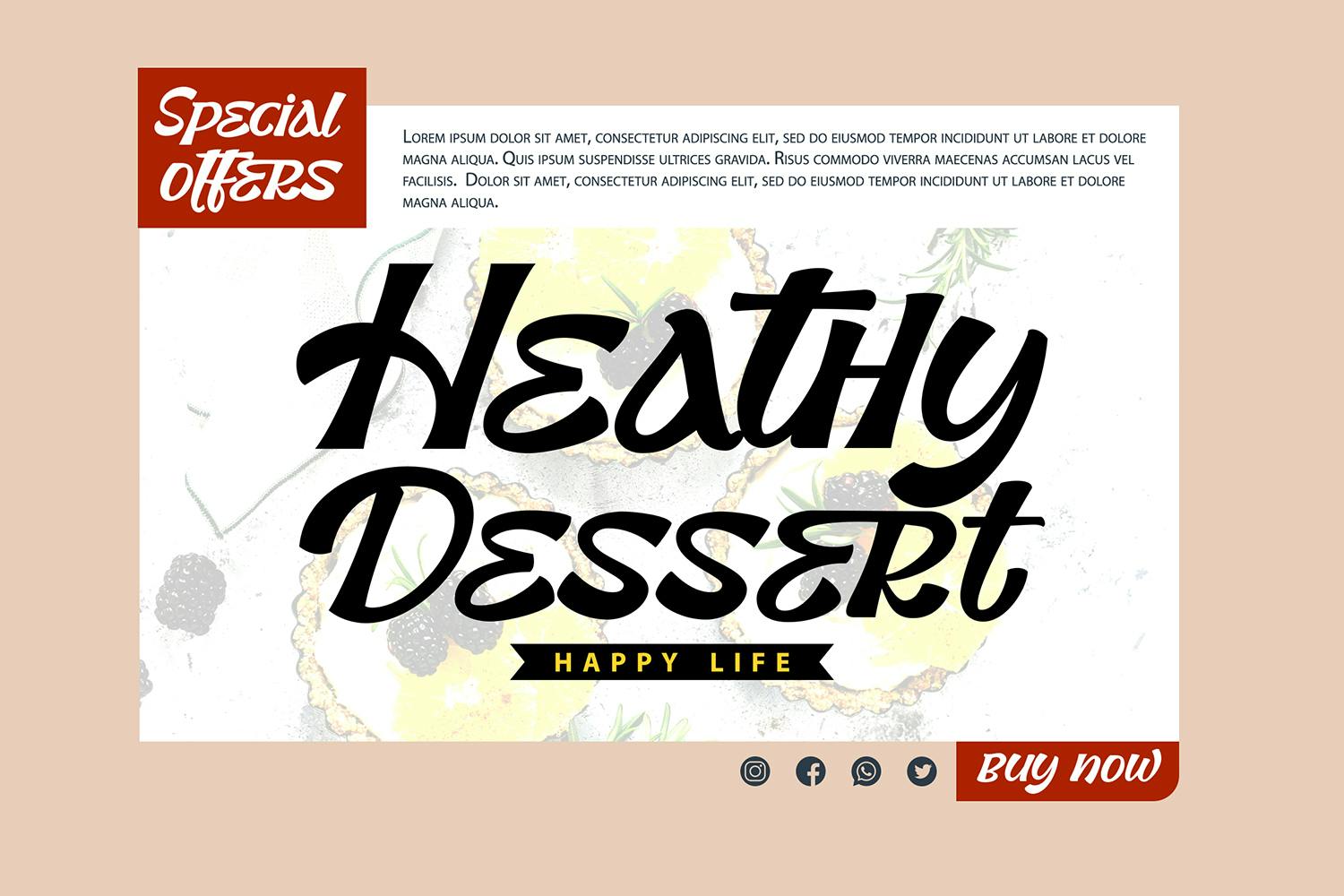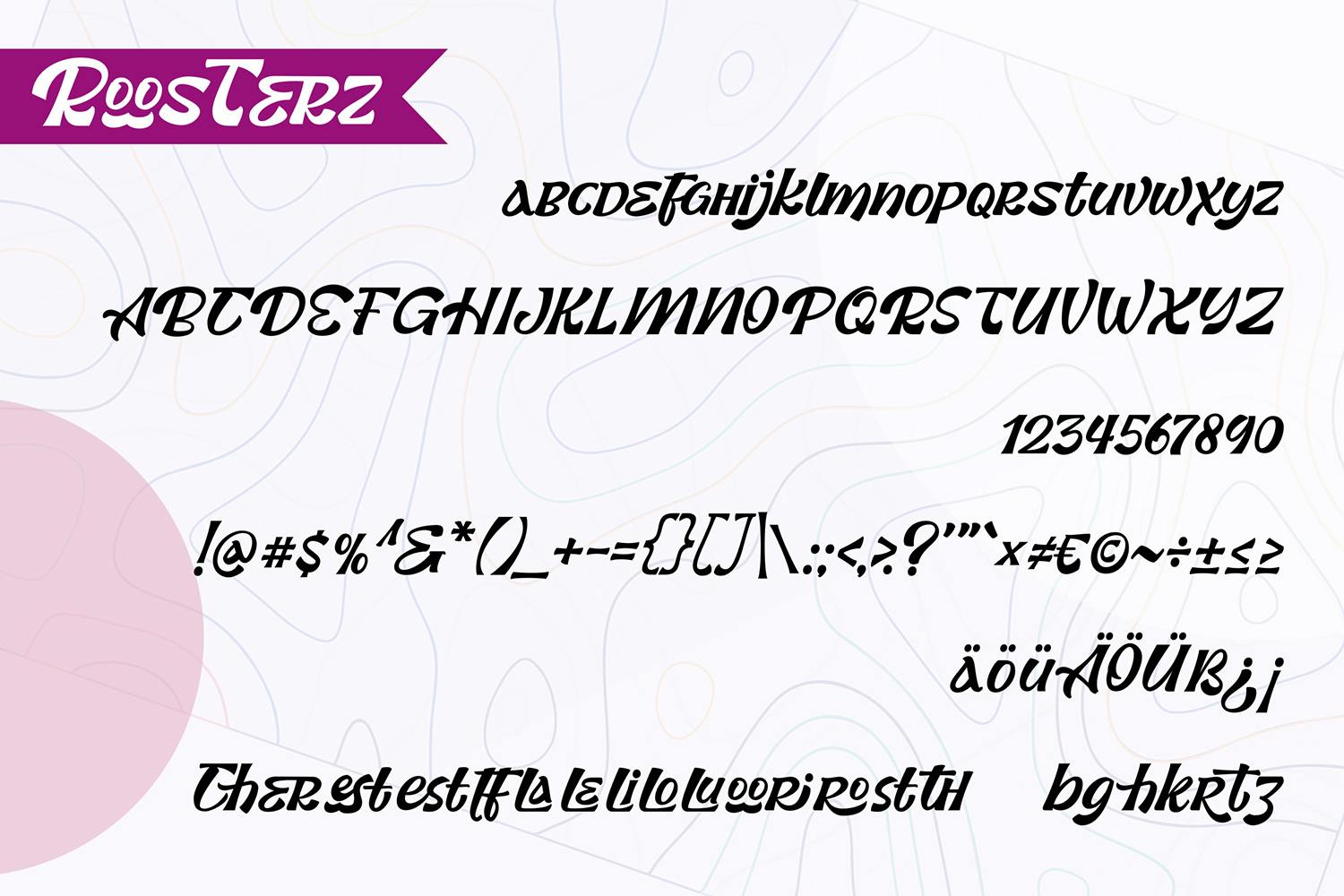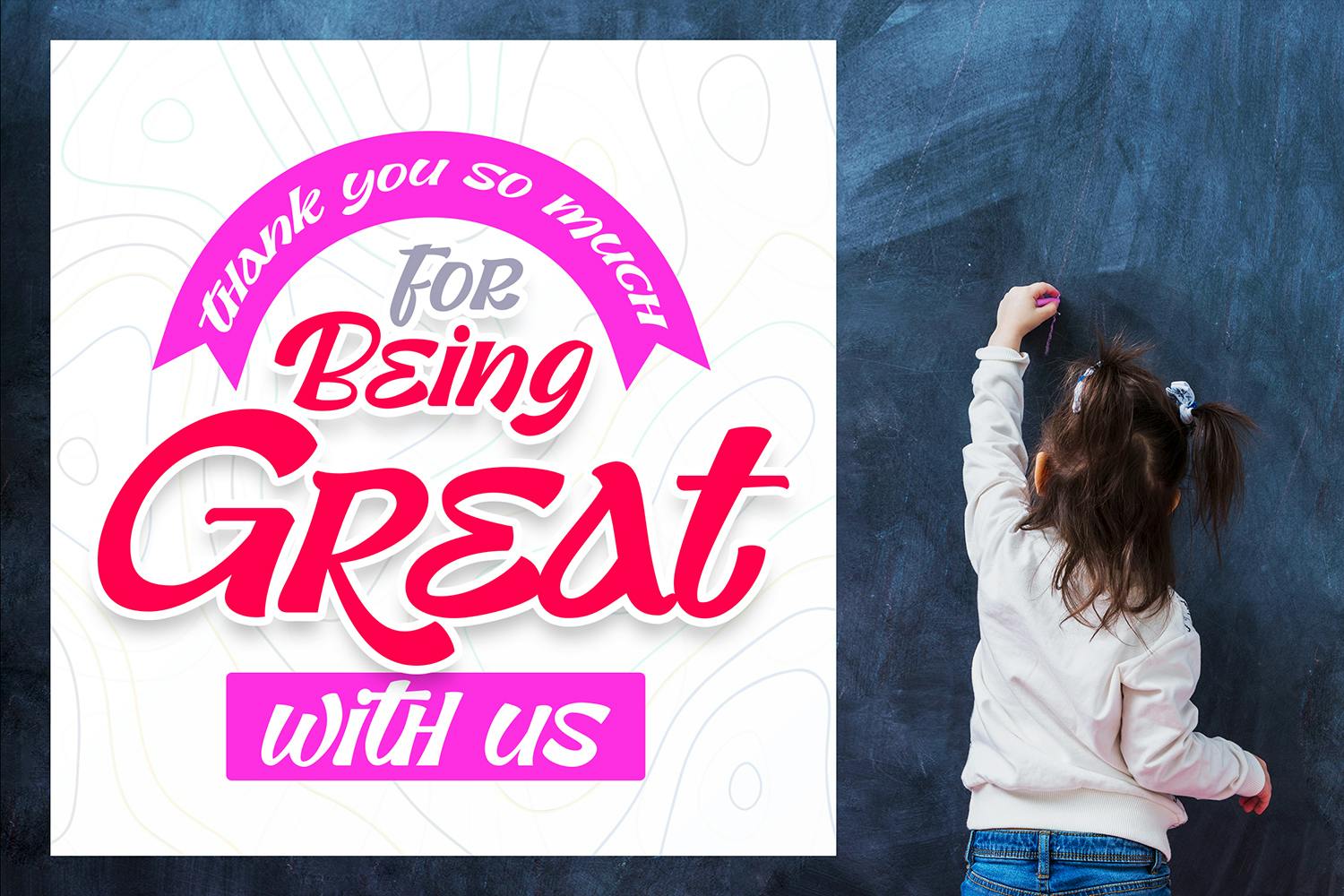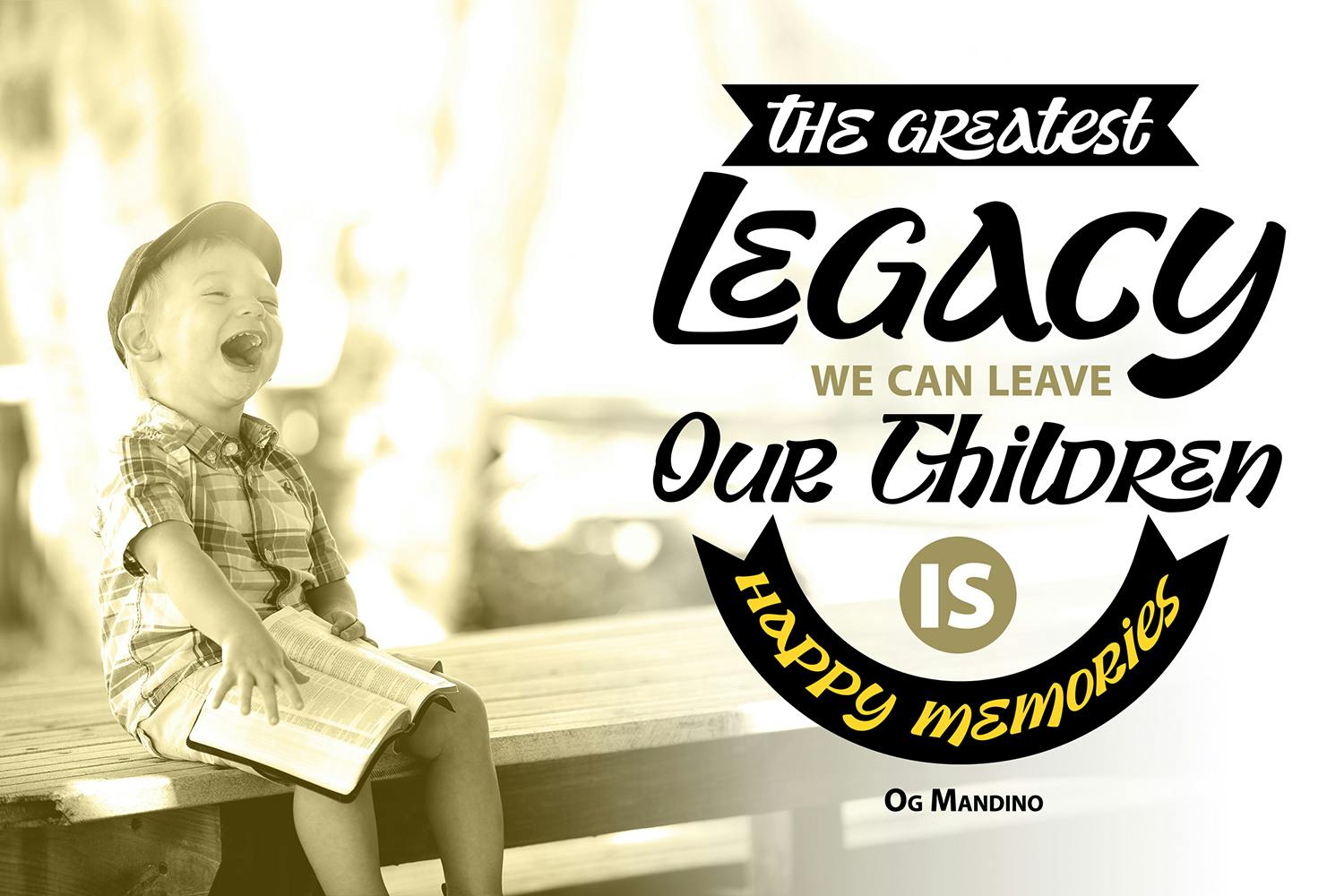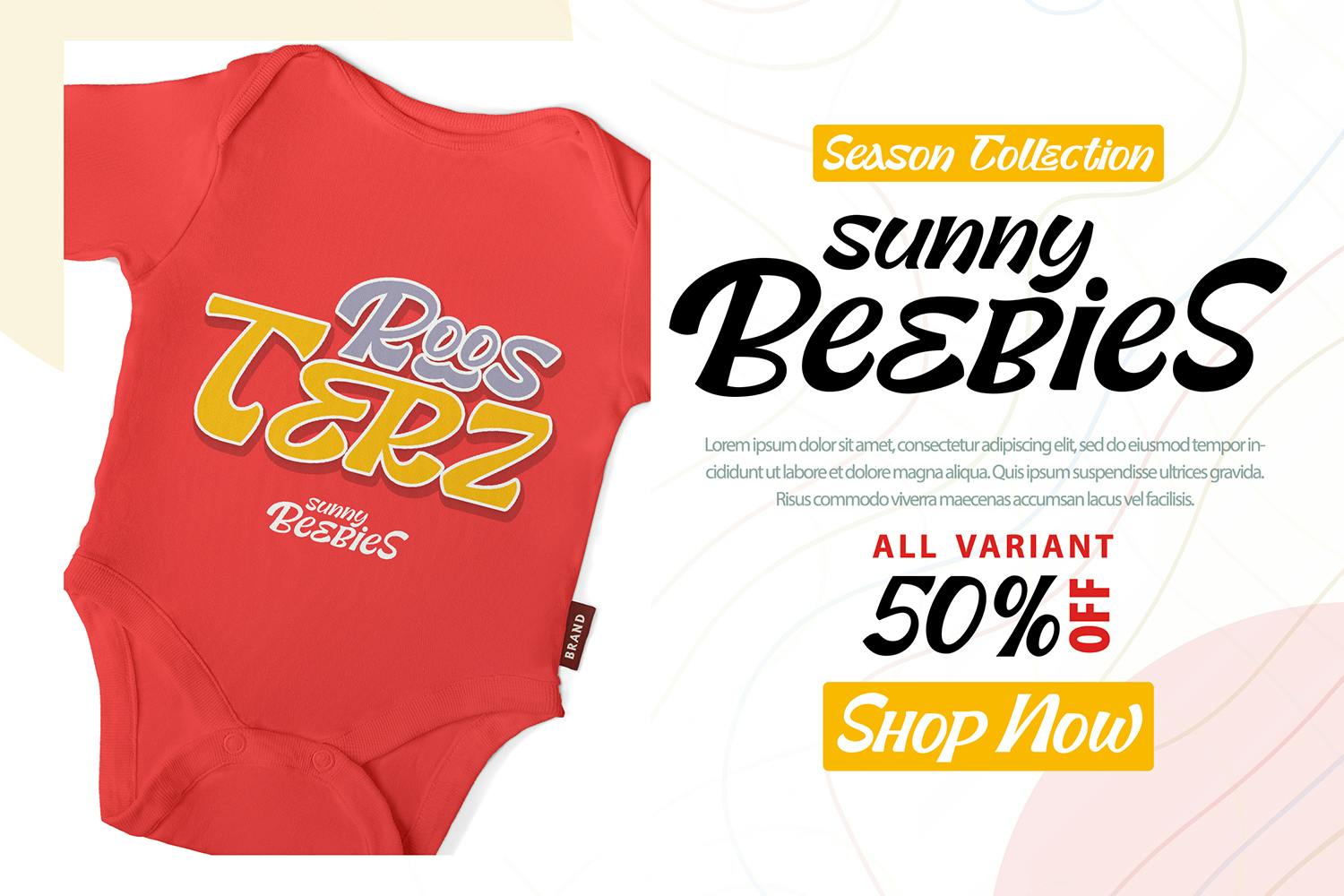
Roosterz | فونت نمایش دستنویس منحصر به فرد با سبک خوشنویسی، بسیار زیبا برای دعوتنامهها، کارتهای تبریک، مواد برندینگ، کارتهای تجاری، نقلقولها، پوسترها و موارد دیگر!
حروف جایگزین به چندین ویژگی Open Type تقسیم شدهاند که شامل مجموعههای سبک، حروف جایگزین، حروف جایگزین متنی، SWASH و Ligature میباشد. ویژگیهای Open Type را میتوانید با استفاده از برنامههای Open Type مانند Adobe Illustrator، Adobe InDesign، Adobe Photoshop، Corel Draw X و Microsoft Word دسترسی پیدا کنید. این فونت دارای کدگذاری PUA یونیکد است (فونتهای بهطور خاص کدگذاری شده) تا همه حروف جایگزین بهراحتی در دسترس باشند.